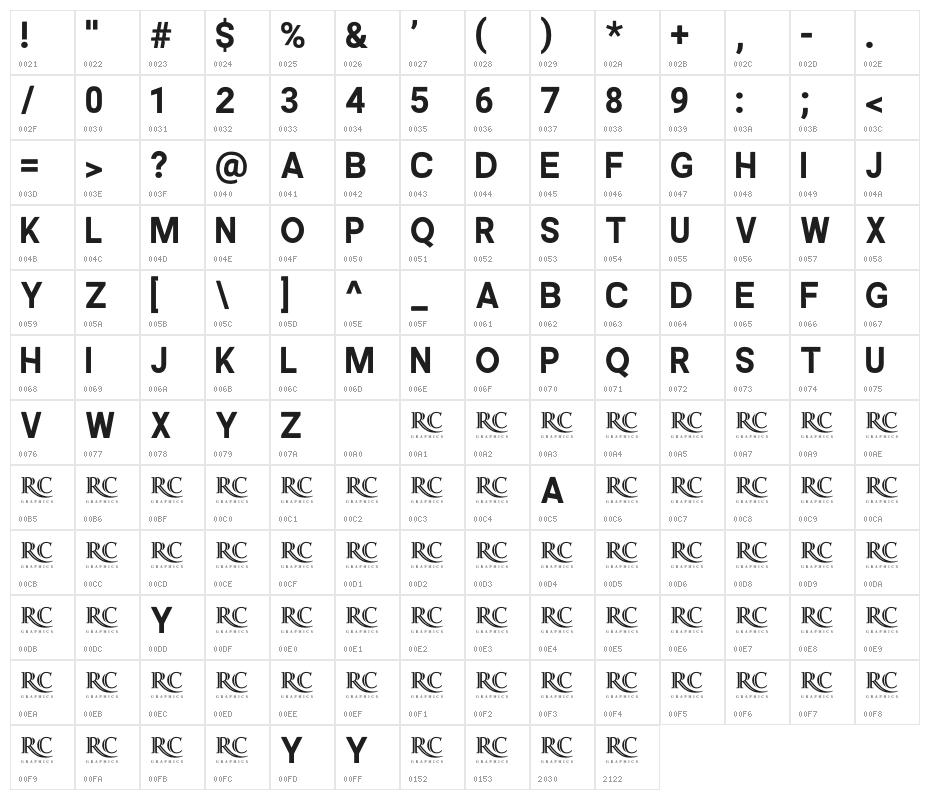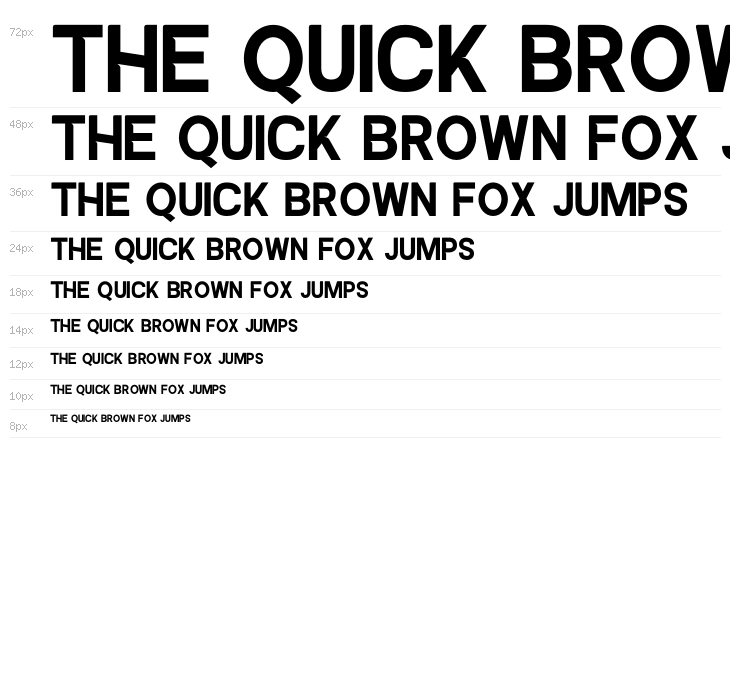
ALISEO Font
| Caso d'uso | Headlines, Logos, Advertising |
| Progetti proposti | Ideal for branding, advertising, headlines, and digital media where a modern and impactful look is needed. |